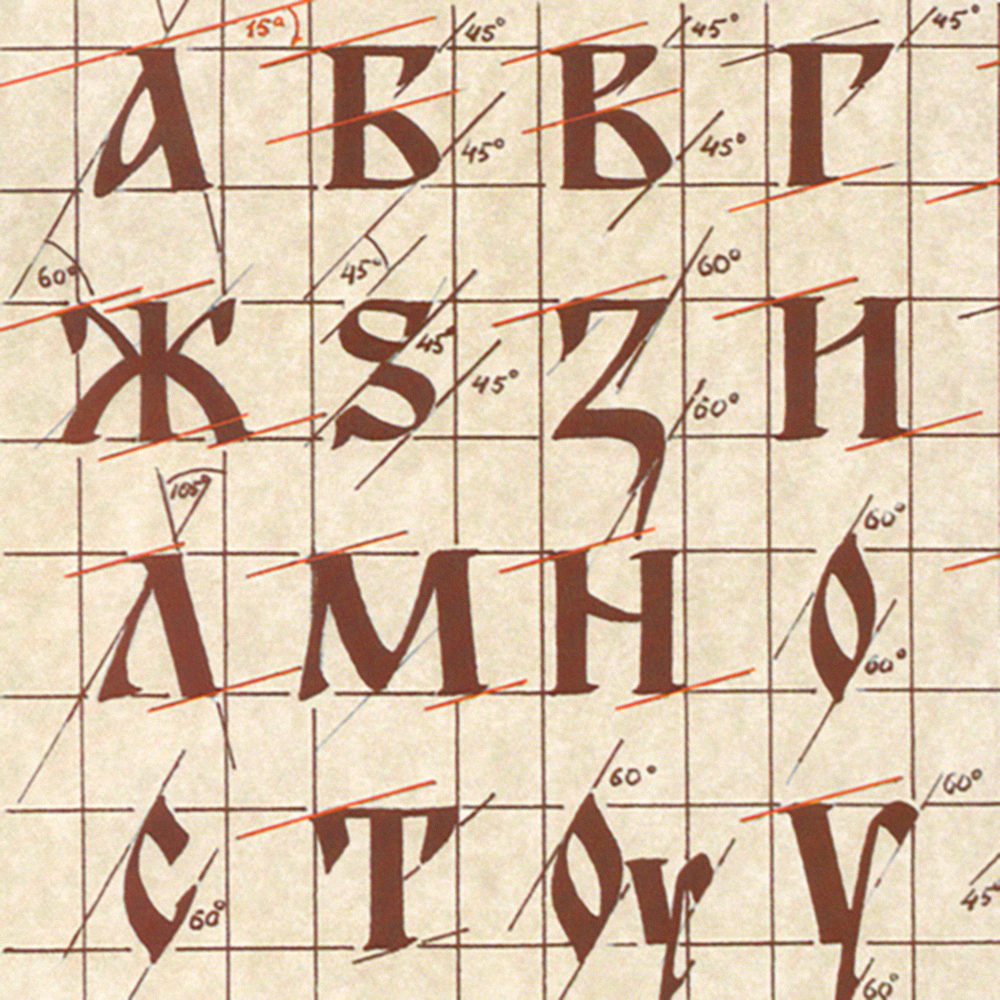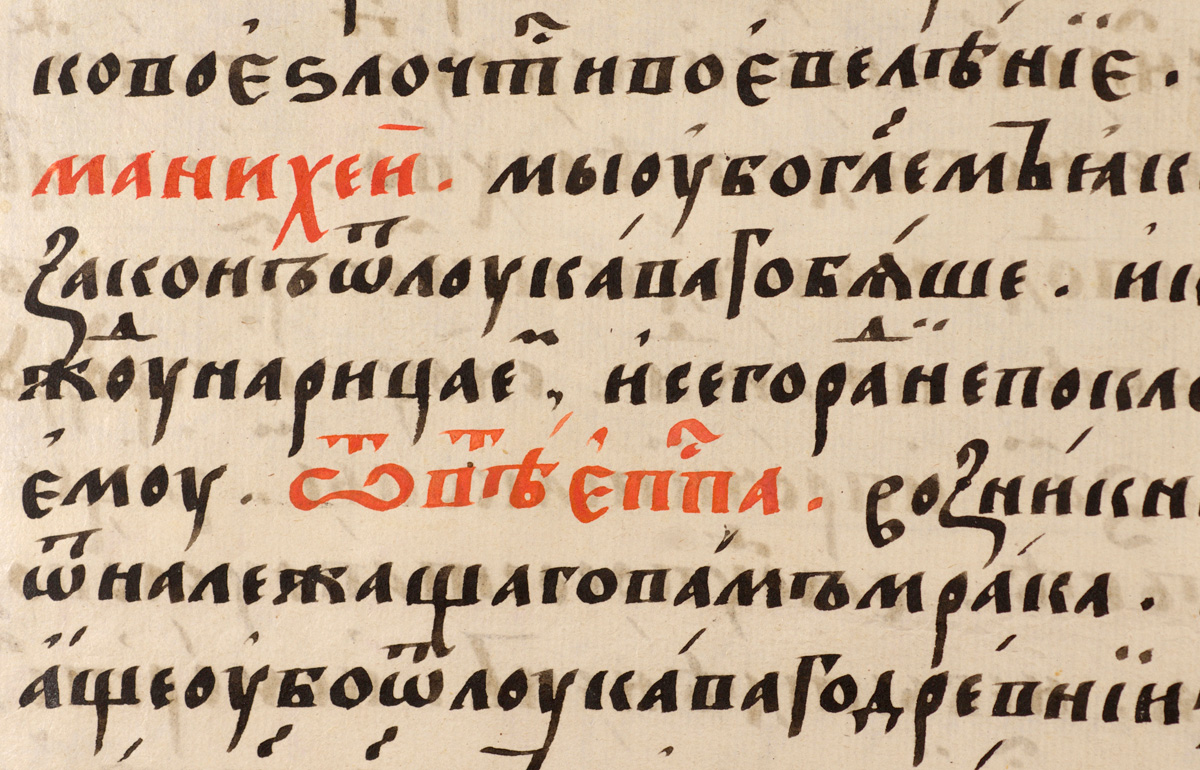
ДРЕВНИЕ РУКОПИСИ. Шрифт древнего Рима в 21 веке. : matveychev_oleg — LiveJournal
Цивилизация древнего Рима оставила нам в наследство один странный парадокс — книги древнего Рима до нас не дошли, наверное из за глубокой древности, а вот шрифт романский не просто дошел, а является самым употребимым шрифтом в 21 веке!
Клавиатура обычно настроена на один из вариантов римского шрифта — не правда ли странное дело?
Романский шрифт очень красив, он прекрасно сбалансирован, он гармоничен! Он легко пишется практически любыми инструментами! Даже майкрософтом! Этот хорошо рассчитанный шрифт есть продукт высокой технологии и большого опыта предыдущих поколений каллиграфов, как и всякая развитая технология она должна иметь свой путь развития, ну примерно как самолеты — сначала были фанерные этажерки, потом первый цельнометаллический самолет, а уж потом «сухой суперджет»! Я так думаю!
livejournal.com/32990.html в коментариях задали простой вопрос, а как выглядят по вашему действительно древние рукописи? Я думаю что вот так —
Как говорится — материал соответствует инструментам и технологиям нанесения… все логично, деревянная плашка и ножичек, ну и шрифт соответствующий!……вот черт….даже пошел покурил… мысль то какая — вот она логика оценки достоверности! Материал, инструмент и технология использования должны соответствовать друг другу! Не много пофилосовствую…. вот если взять пластиковую панель и на ней гвоздем криво нацарапать — вася, где здесь алогичность, не правильность — материал! Но если на березке тем же гвоздем красивым шрифтом романским нацарапать, нет даже так — написать — ВАСЯ! То опять будет нарушение логики! И если на березке криво выжечь лазером — того же васю, будет опять нарушение логики! По этому корга я вижу надпись на камне романским шрифтом я вижу нарушение логики! Постараюсь сейчас это доказать.
Вот древняя руническая надпись — все логично, кривенько
Вот древняя этрусская надпись, то же самое сикось накось и сбоку поперек!
Но как же так — этруски создали Рим, а писать как люди так и не научились — дикие, что с них возьмешь!
Что такое шрифт — это устоявшаяся форма написания, общепринятая, распространенная, стандартная как по ГОСТу! Что мы и видим в Риме все надписи выдержаны в одном стиле одним шрифтом!
Для формирования шрифта нужно время и куча бумаги, что бы писать, даже один человек за долгое время реального писарства вырабатывает как бы свой шрифт — мы это называем почерк, вспомните как раньше в школе нам пытались поставить почерк — чистописанием и что, какой он у Вас теперь?
Для формирования шрифта очень важен материал на котором пишешь и инструмент которым пишешь.
Вот берестяная грамота, материал очень сложный для письма так как имеет резко выраженную фактуру, по этому и определяет инструмент — специальный ножик и письмо — резы, причем обратите внимание — написано поперек волокон, а иначе ножик будет прорезать бересту и сложно будет четко закончить линию.
.. вроде бы все логично, но есть в этом примере одно но — наклон букв (!!!) писал человек которого учили чистописанию на линованной в наклон тетрадке, привык он так! Я честно говоря не знаю, что это за береста и как она датируется но….
Вот эта береста уже больше похожа на реальность — буковки пляшут.
Вот еще один древний текст. Папирус, написано палочкой, посмотрите как по мере написания палочка высыхает и буквы не прописаны, но почерк хороший, нам бы такой каждому — значит школа письма есть. Но в общем то все логично — материал, ему соответствует инструмент — палочка и шрифт — обычная пропись. Вот если в 20 веке так написать логично очень сложно датировать будет! Значит либо очень хорошая подделка либо настоящая древняя надпись!
Вот например классика письма пером гусиным — от силы нажима меняется ширина черты, от узкого до очень широкого — перо мягкое и позволяет, а вот например металлическое не позволяет, ширина черты определяется шириной пера — шире не получится!
А вот готика но написанная металическим пером — ширина и черта торцом одинаковые везде!
Надо немного рассказать о перьях для письма, современных, плакатных!Так будет понятнее что я имею ввиду!
Вот простые перья для письма
А это перья для каллиграфии, они широкие, что позволяет делать букву разной по толщине на разных участках — вертикальные черты и горизонтальные
Вот эта надпись либо пером гусиным но широко отрезанным, плоско или металическим но еще очень низкого качества, то есть эта надпись древняя.
Калиграфия, работа широким пером, очень хорошо видно это на символах в арабесках в виде кубиков!
Вот так калиграф пишет пером сверху вниз — широко в бок узко!
А теперь посмотрите на этот шедевр калиграфии — этот шрифт мог появиться только с появлением печати, руками так писать можно но очень сложно, а в рукописи важно время написания, не только качество, а вот если шрифты уже сделаны из металла то нет проблем!